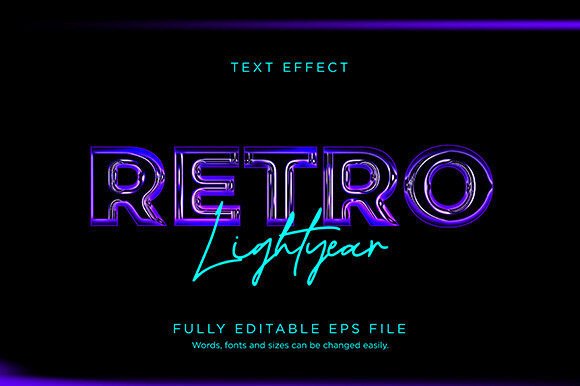
Retro Text Effect Font Type Vector
Việc tìm kiếm các thành phần thiết kế phù hợp có thể là một thách thức, nhưng Retro Text Effect Font Type Vector cung cấp một bộ sưu tập đặc biệt giúp nâng tầm công việc của bạn ngay lập tức.
Được chế tác với độ chính xác cao, Retro Text Effect Font Type Vector cung cấp các vector sạch, kiểu chữ mượt mà và giấy phép thương mại để bạn yên tâm.
Cho dù bạn đang tạo sản phẩm POD (In theo yêu cầu), thiệp mời đám cưới hay đồ họa mạng xã hội, Retro Text Effect Font Type Vector đều là một sự lựa chọn lý tưởng.